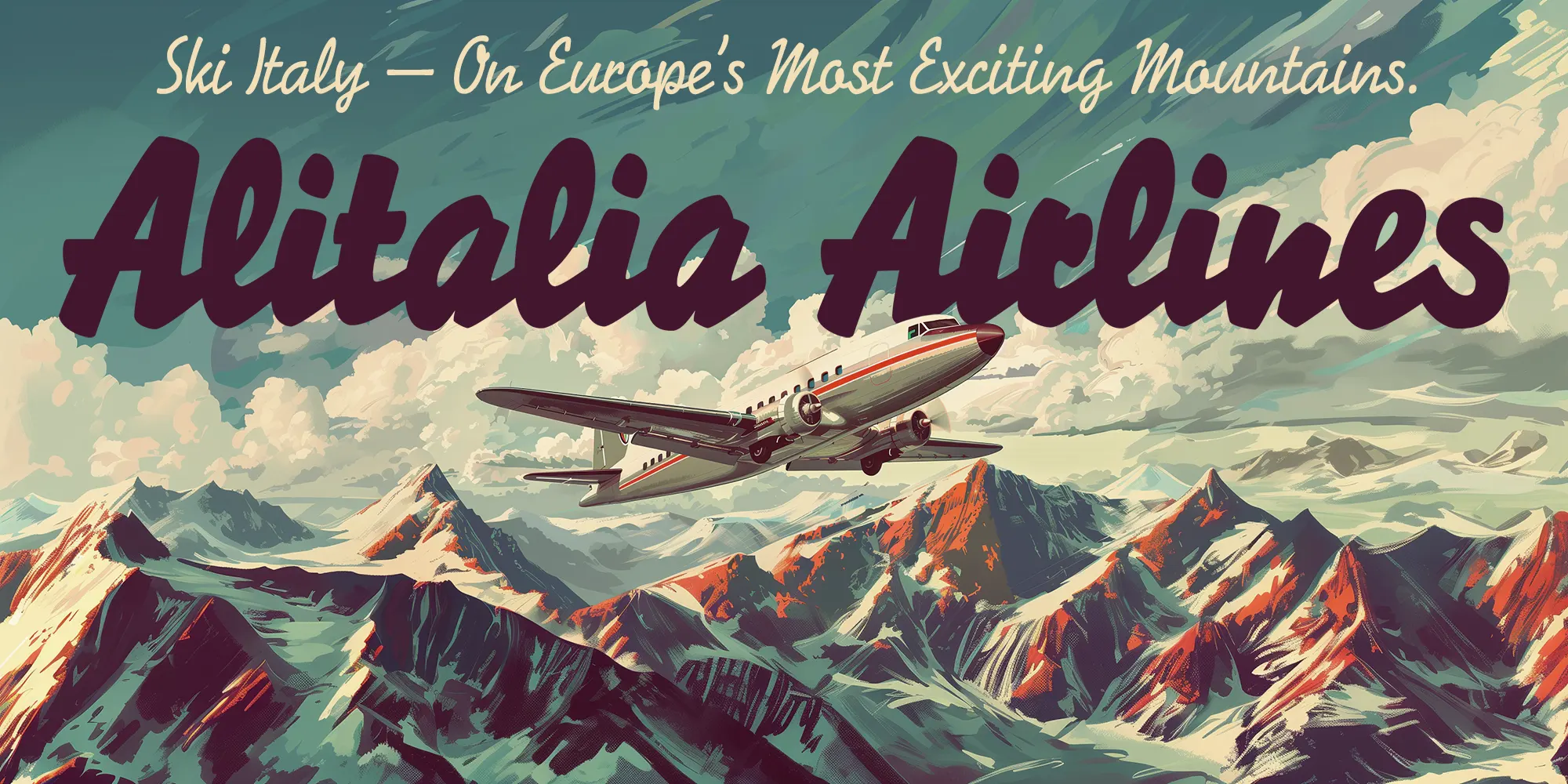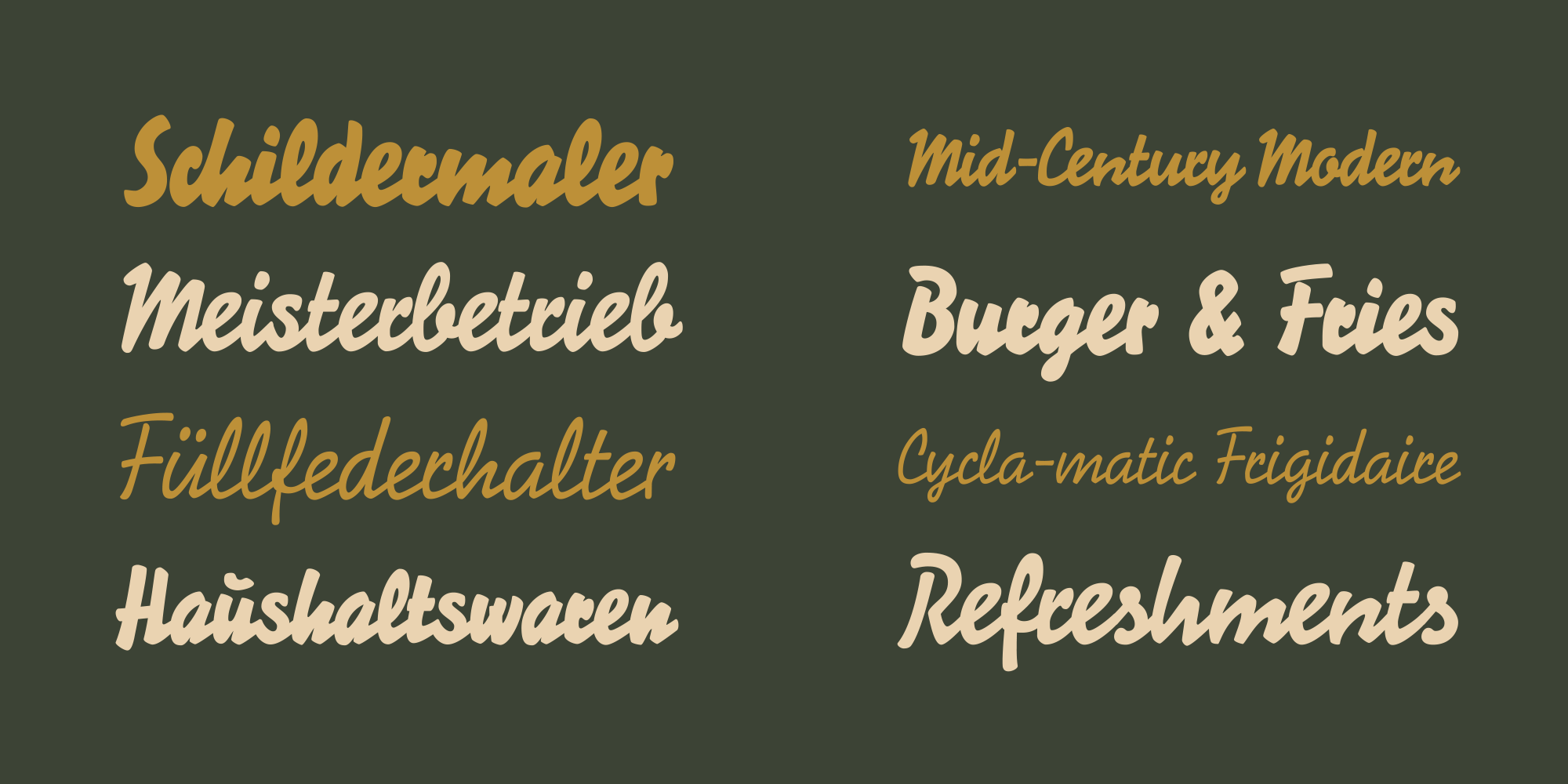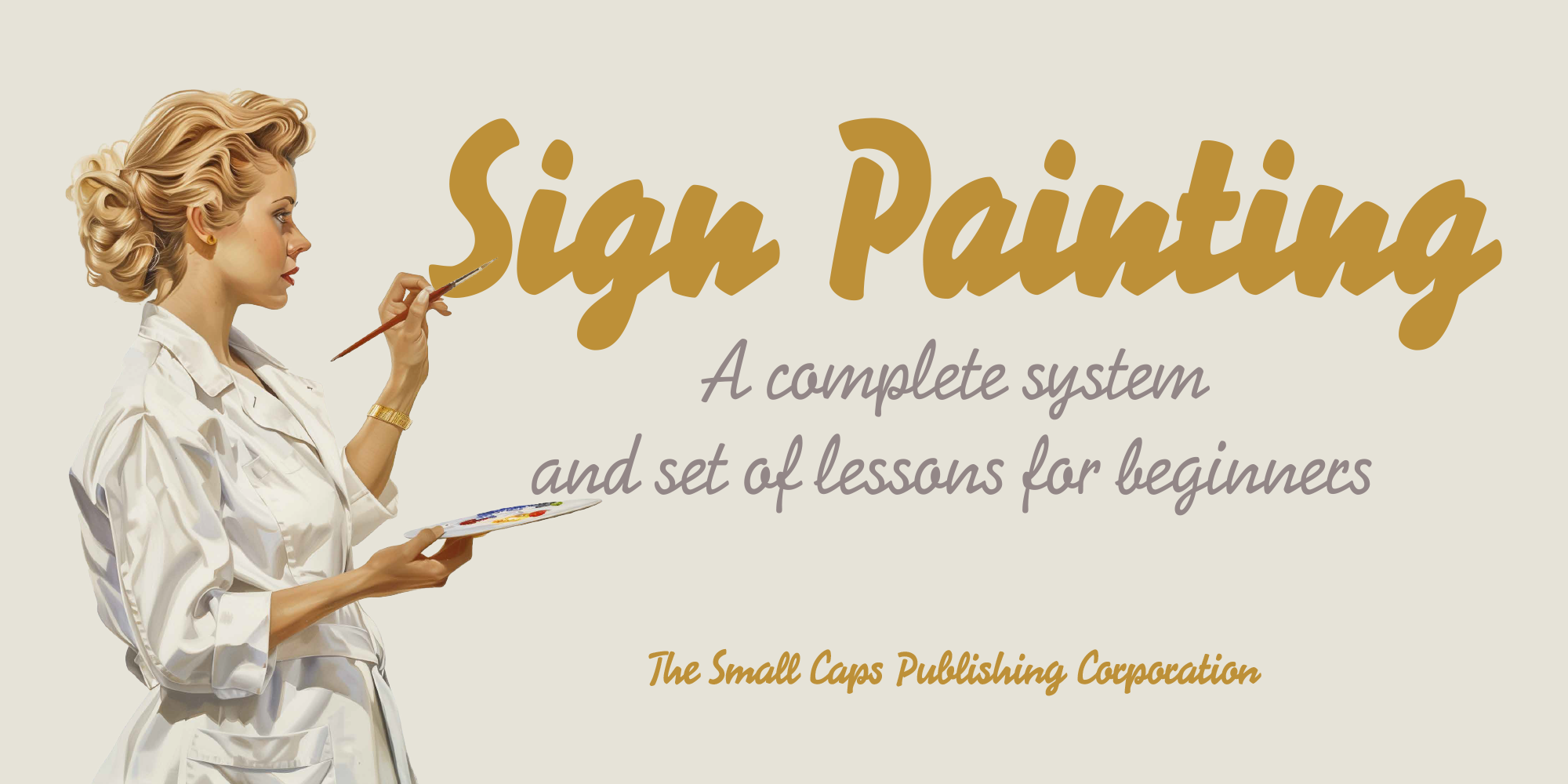
- Antiqua Schreibschrift
FDI Lettograph ist eine vollständige Digitalisierung der Berthold Signal, die über eine Kickstarter-Kampagne möglich gemacht wurde und nun kostenlos nutzbar ist. Enthalten sind alle drei Original-Strichstärken bzw. eine variable Schrift, die zwischen den drei Varianten interpoliert. Über eine kontextbedingte Zeichenersetzung per OpenType werden automatisch die bestmöglichen Zeichenverbindungen ausgewählt und im Gegensatz zu vielen anderen digitalen Schreibschriften werden unnatürliche Verbindungsschwünge am Zeichenende unterdrückt, wenn kein Buchstabe mehr folgt.